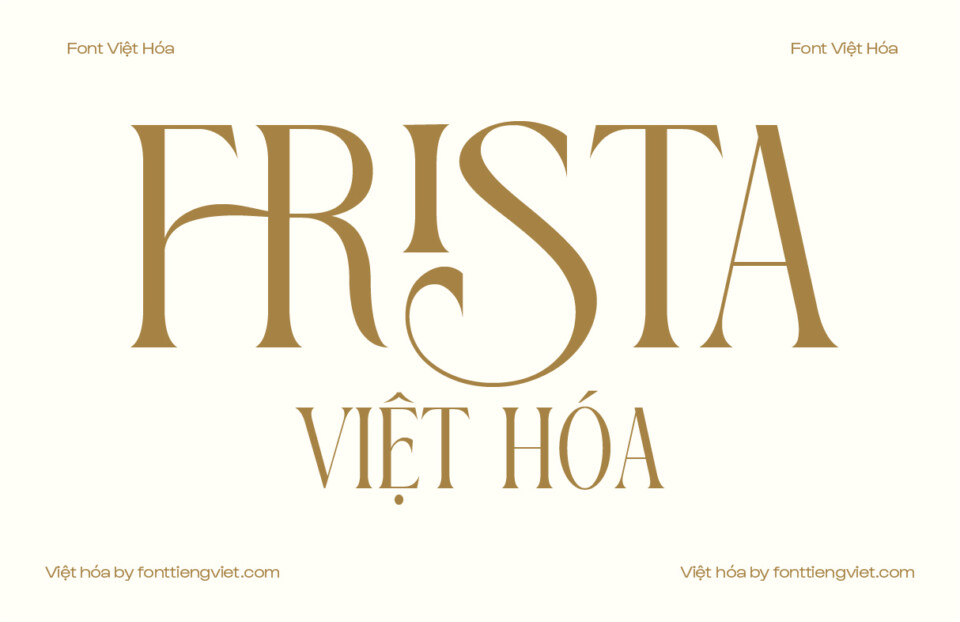
Font Việt hóa 1FTV VIP Frista: Lựa chọn hoàn hảo cho thiết kế học đườngGiới thiệu về Font Việt hóa 1FTV VIP FristaTrong thế giới thiết kế đồ họa hiện đại, việc lựa chọn một bộ Font Miễn Phí chất lượng luôn là ưu tiên hàng đầu của các bạn học sinh và giáo viên. Font Việt hóa 1FTV VIP Frista nổi lên như một giải pháp tối ưu, mang đến sự kết hợp tinh tế giữa nét đẹp cổ điển và hơi thở hiện đại. Đây là bộ phông chữ được tinh chỉnh kỹ lưỡng để phù hợp với bảng mã tiếng Việt, giúp người dùng dễ dàng trình bày các bài thuyết trình, báo cáo hay thiết kế thiệp mời mà không lo lỗi font. Với cấu trúc các nét thanh mảnh nhưng chắc chắn, bộ font này tạo nên một cảm giác chuyên nghiệp, thanh lịch và cực kỳ dễ nhìn trên cả màn hình máy tính lẫn bản in giấy.Đặc điểm nổi bật của Font Việt hóa 1FTV VIP FristaThiết kế hiện đại và tinh tếFont Việt hóa 1FTV VIP Frista sở hữu những đường nét bo tròn mềm mại kết hợp với các góc cạnh sắc sảo, tạo nên một tổng thể hài hòa. Điều này giúp bộ chữ không chỉ phù hợp cho các văn bản hành chính mà còn rất ấn tượng khi dùng làm tiêu đề cho các ấn phẩm truyền thông học đường như tờ rơi hay poster câu lạc bộ. Sự cân đối trong tỉ lệ giữa các ký tự giúp văn bản duy trì được nhịp điệu đọc ổn định, không gây mỏi mắt cho người xem trong thời gian dài.Khả năng tương thích và Việt hóa hoàn chuẩnĐiểm mạnh nhất của Font Việt hóa 1FTV VIP Frista chính là sự đầy đủ của các dấu thanh tiếng Việt. Người dùng sẽ không gặp phải tình trạng các dấu bị lệch vị trí hay sai định dạng vốn thường thấy ở các font nguyên bản chưa được chỉnh sửa. Nhờ sự tỉ mỉ trong quá trình Việt hóa, mọi ký tự từ đơn giản đến phức tạp đều hiển thị mượt mà trên các phần mềm phổ biến như Microsoft Word, PowerPoint hay Canva. Điều này hỗ trợ đắc lực cho các bạn học sinh trong việc hoàn thiện bài tập lớn một cách chỉn chu nhất.Ứng dụng thực tiễn trong môi trường giáo dụcSử dụng trong bài giảng và thuyết trìnhGiáo viên có thể sử dụng Font Việt hóa 1FTV VIP Frista để làm mới các slide giảng dạy của mình. Sự thanh thoát của font chữ giúp các nội dung kiến thức trở nên sinh động và thu hút sự chú ý của học sinh hơn. Khi các đề mục lớn được trình bày bằng bộ font này, chúng tạo ra một điểm nhấn thị giác rõ ràng, giúp học sinh dễ dàng hệ thống lại kiến thức đã học trên lớp.Thiết kế ấn phẩm và tài liệu học tậpĐối với các dự án nhóm hoặc các tờ báo tường, việc sử dụng Font Việt hóa 1FTV VIP Frista sẽ nâng tầm thẩm mỹ cho sản phẩm. Font chữ này rất “ăn nhập” với các tông màu pastel nhẹ nhàng hoặc các bố cục trang trí đơn giản. Ngoài ra, tính ứng dụng cao của nó còn thể hiện qua việc in ấn tài liệu tham khảo, giúp các văn bản dài trở nên thông thoáng và dễ tiếp cận hơn đối với người đọc.Kết luận về bộ Font Việt hóa 1FTV VIP FristaViệc sở hữu một bộ phông chữ đẹp không chỉ giúp nâng cao hiệu quả giao tiếp mà còn thể hiện sự tôn trọng đối với người xem. Font Việt hóa 1FTV VIP Frista thực sự là một công cụ đắc lực, giúp biến những ý tưởng sáng tạo thành hiện thực một cách dễ dàng. Hy vọng rằng qua bài viết này, các bạn đã có thêm một lựa chọn uy tín cho kho tài nguyên thiết kế của mình. Đừng quên truy cập trang web để cập nhật thêm nhiều bộ Font Miễn Phí, Font Việt Hóa, Font Việt hóa 1FTV VIP Frista chất lượng khác phục vụ cho việc học tập và giảng dạy nhé.
Font Việt hóa 1FTV VIP Frista